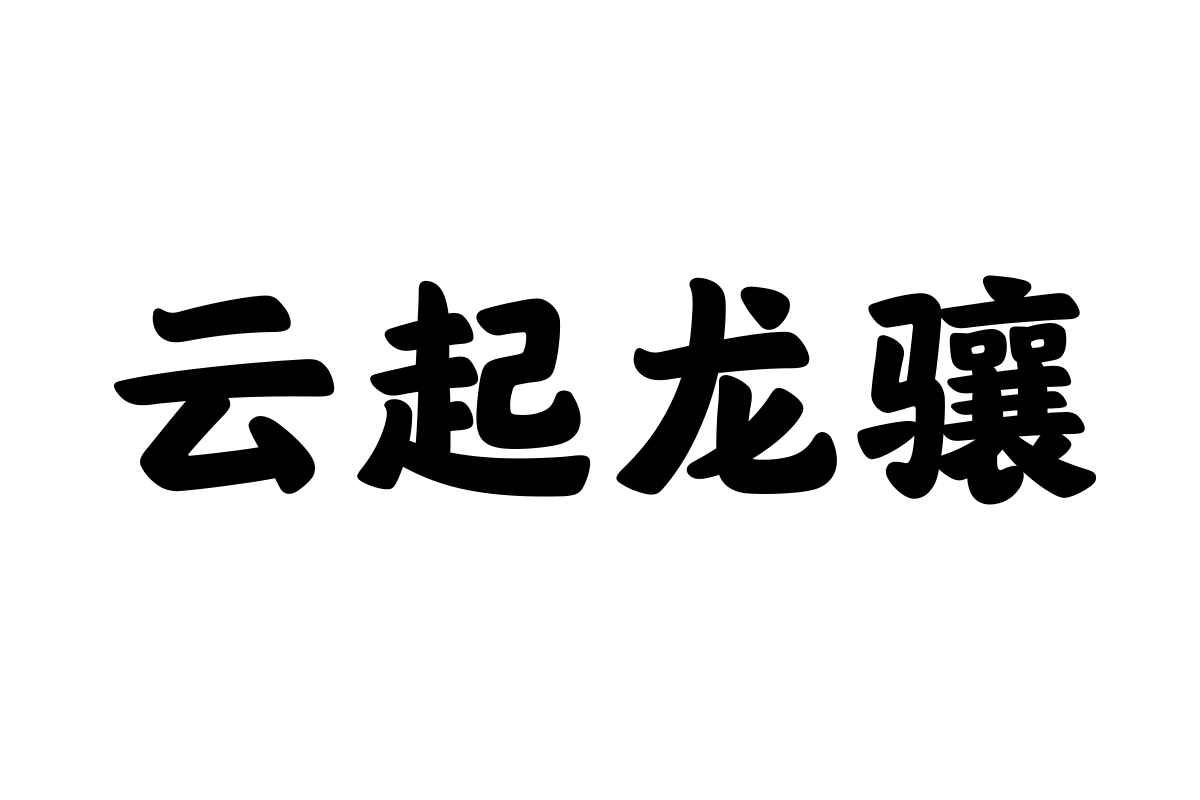
汉仪唐美人-95是一款具有浓郁中国风的字体,其设计灵感来源于唐代的美女。这款字体笔画流畅,结构紧凑,给人一种优雅而高贵的感觉。同时,它还融入了一些现代的元素,使得整体风格更加时尚。
汉仪唐美人-95的特点如下:
1. 字形饱满:这款字体的字形饱满,线条流畅,给人一种优美的视觉享受。
2. 结构紧凑:汉仪唐美人-95的结构紧凑,笔画紧密相连,使得整个字体看起来更加协调。
3. 风格独特:这款字体的设计灵感来源于唐代的美女,因此具有浓郁的中国风特色。
4. 易于阅读:虽然汉仪唐美人-95具有一定的艺术性,但整体上仍然保持了良好的可读性,适合用于书籍、杂志等需要清晰易读的场合。
总的来说,汉仪唐美人-95是一款具有独特魅力的字体,无论是在设计还是在日常使用中都有很好的表现。